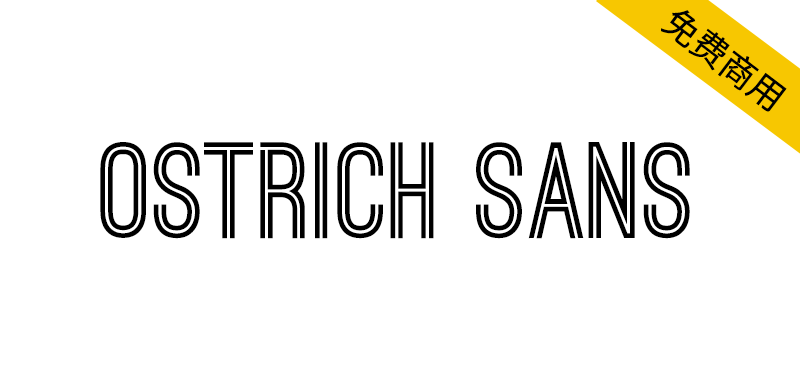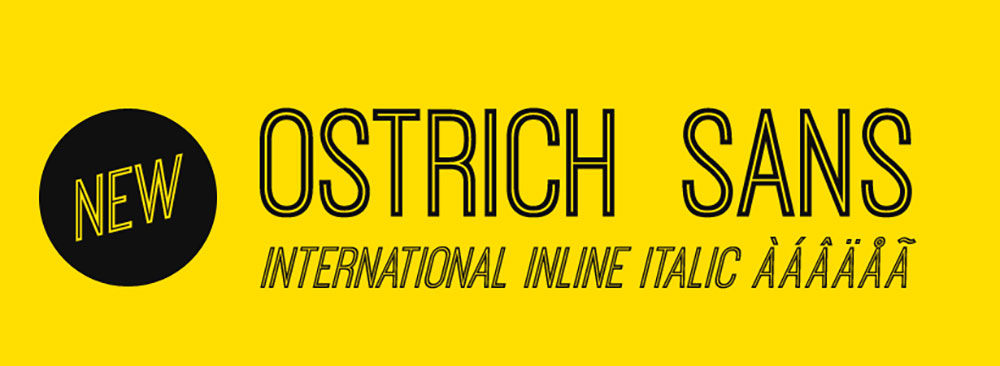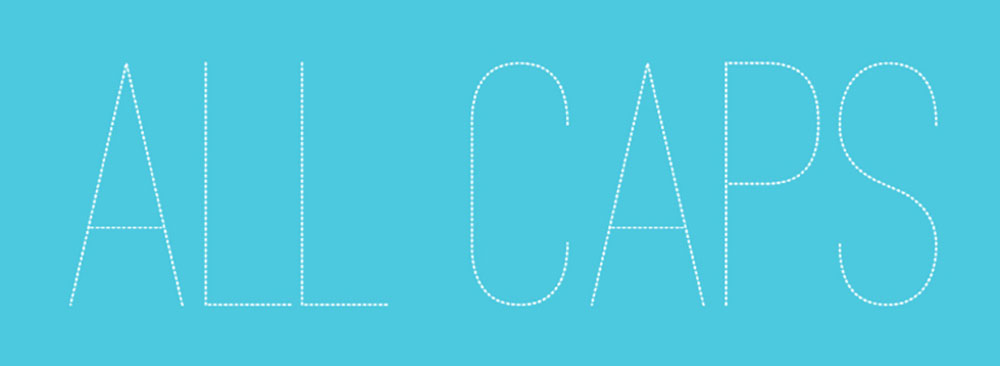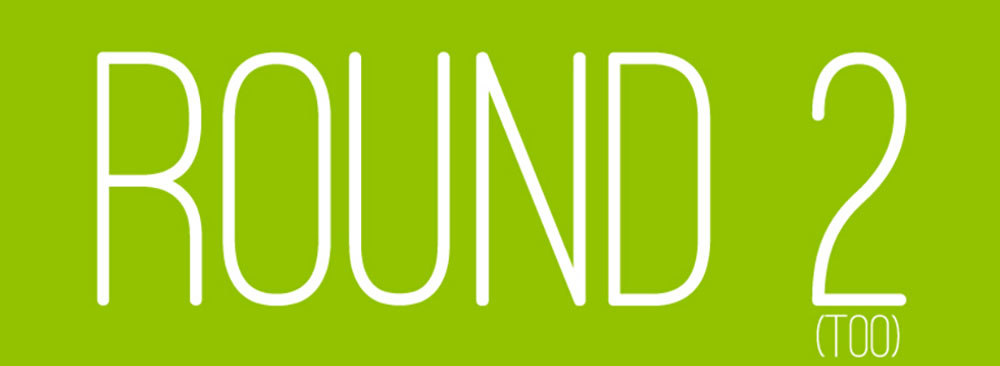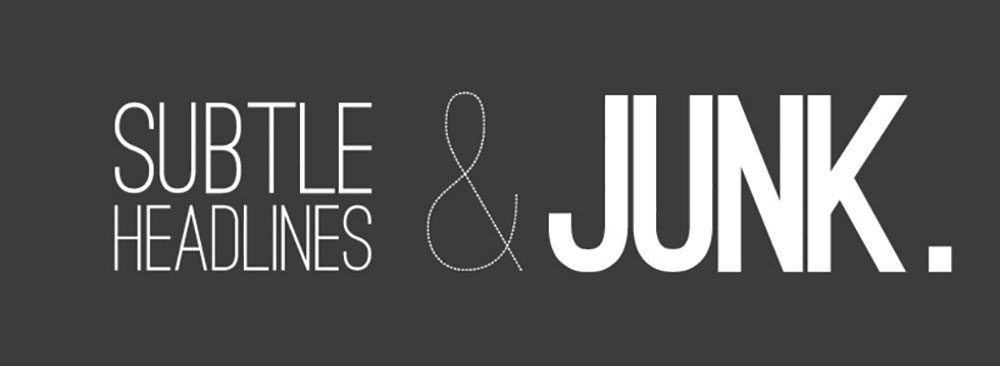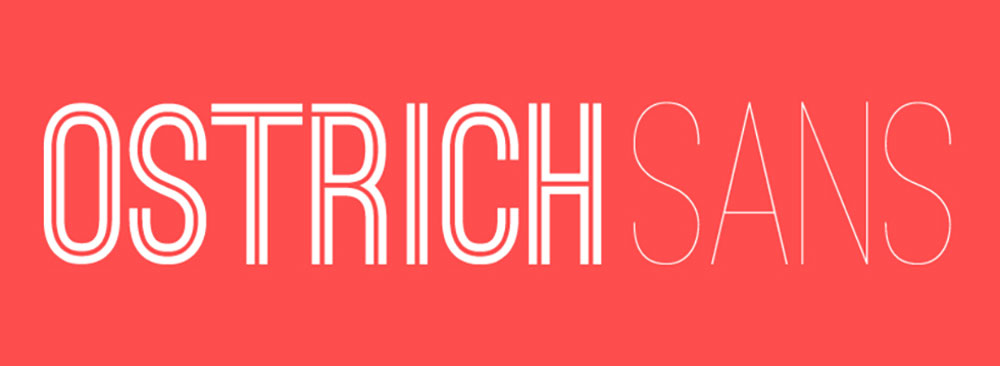
Ostrich Sans是一款线条修长的华丽的现代无衬线字体,提供丰富多样的字重与风格:虚线(细体)、圆角(中等)、超细、常规、粗体(赛道风格双线)、特粗、空心(含斜体)、厚重(圆润)。
A gorgeous modern sans-serif with a very long neck. With a whole slew of styles & weights:Dashed (thin),Rounded (medium),Ultra light,Normal,Bold (race track style double lines),Black,Inline (with italics),Heavy (round)